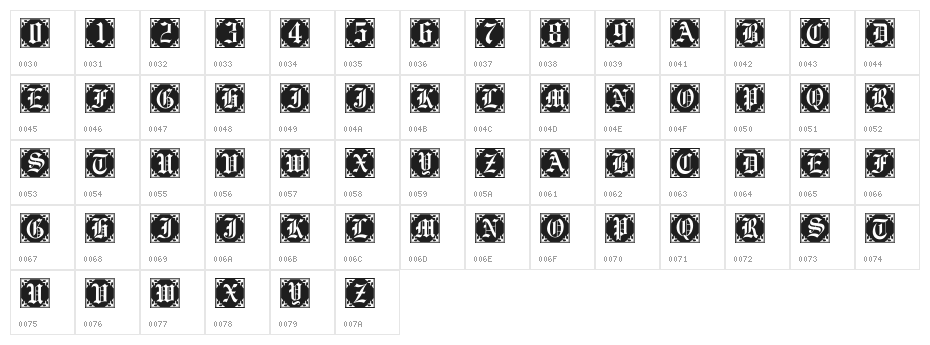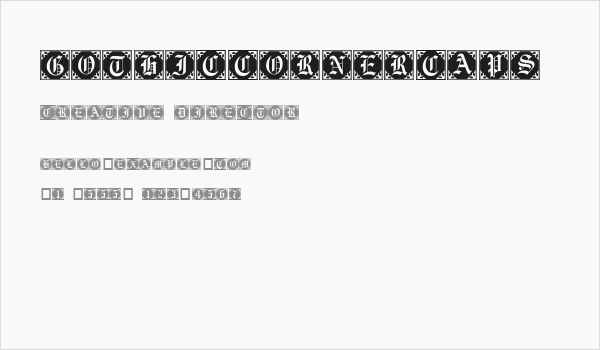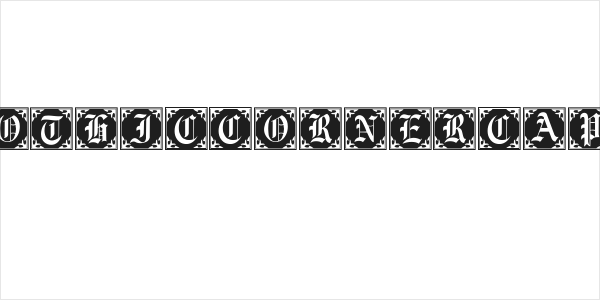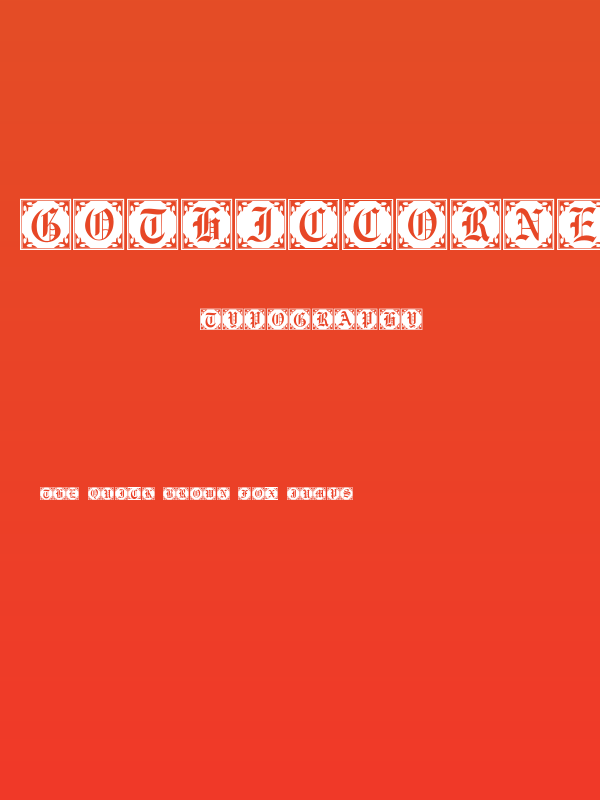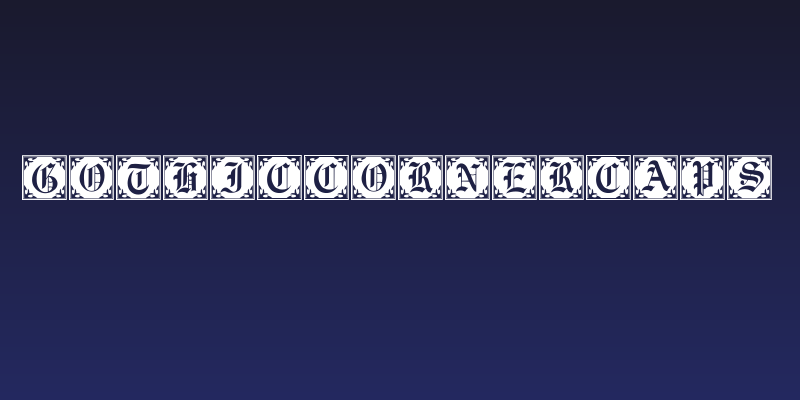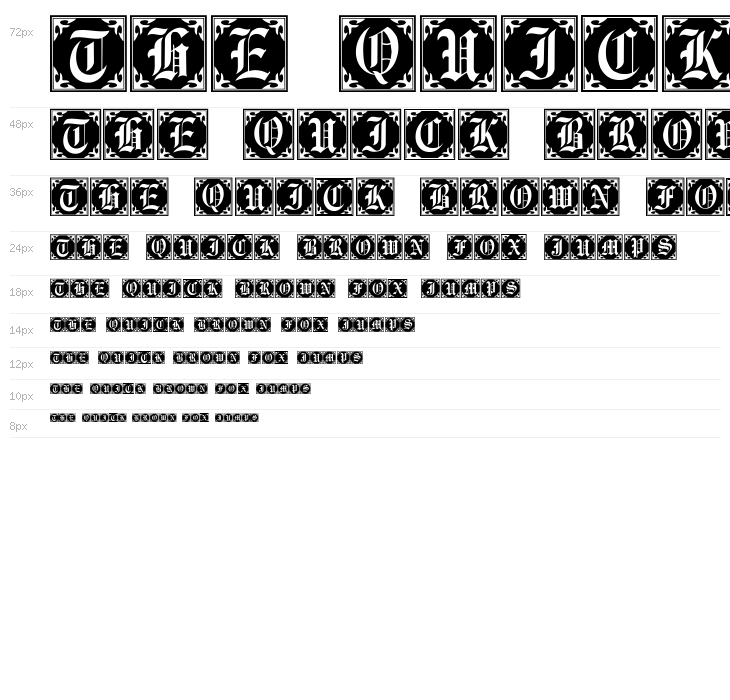
GothicCornerCaps Font
| Gesamtstil | Vintage |
| Anwendungsfall | Headlines, Logos, Decorative purposes |
| Vorgeschlagene Projekte | Ideal for historical themed designs, book covers, posters, and branding that seeks a medieval or dramatic touch. |